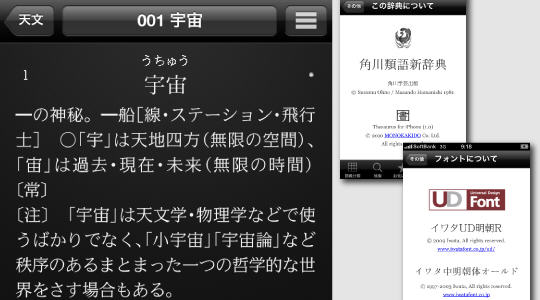
iPhone アプリケーション『角川類語新辞典』 |
| 使用書体 | イワタUD明朝、イワタ中明朝体オールド |
| 事例紹介文 | 「角川類語新辞典」は、わが国初の画期的シソーラスとして現代日本語約 49,000語を意味別に分類・体系化した、角川学芸出版の「類語新辞典」の iPhone アプリケーションです。 適切な言葉が思い浮かばないとき、同じ語を別の言葉に言いかえたいとき、そんなときに役立つ辞典です。 http://www.monokakido.jp/iphone/ruigo.html |
【企業紹介】 物書堂はMac OS X / iPhone OS 用ソフトウェアの企画・開発・販売を手がけるソフトウェア会社です。代表的な製品であるiPhone OS 用の「大辞林」では「2009年度グッドデザイン賞」、「第3回 JEPA 電子出版アワード大賞」を受賞しています。 【ユニバーサルデザインへの取り組み】 iPhone アプリケーション「角川類語新辞典」ではイワタUD明朝を採用しました。製品の仕様を考える際には、操作のしやすさだけでなく、コンテンツの読みやすさ、コンテンツとの親和性も考慮して書体を選択しています。より多くのお客様にアプリケーションを活用していただくためにユニバーサルデザインは非常に重要であると考えています。 【イワタUDフォントを選択した理由】 類語辞典では複数の類語から目的に適ったものを見つける必要があるため、一覧性を高める必要があります。しかしiPhoneの小さな画面で一覧性を高めるためには文字が小さめになってしまいます。そういった場面にイワタUD明朝体を用いることで、小さな文字でも高い可読性を保つことが可能になりました。また可読性の高い自然なデザインには思考を妨げないというメリットもありました。 |